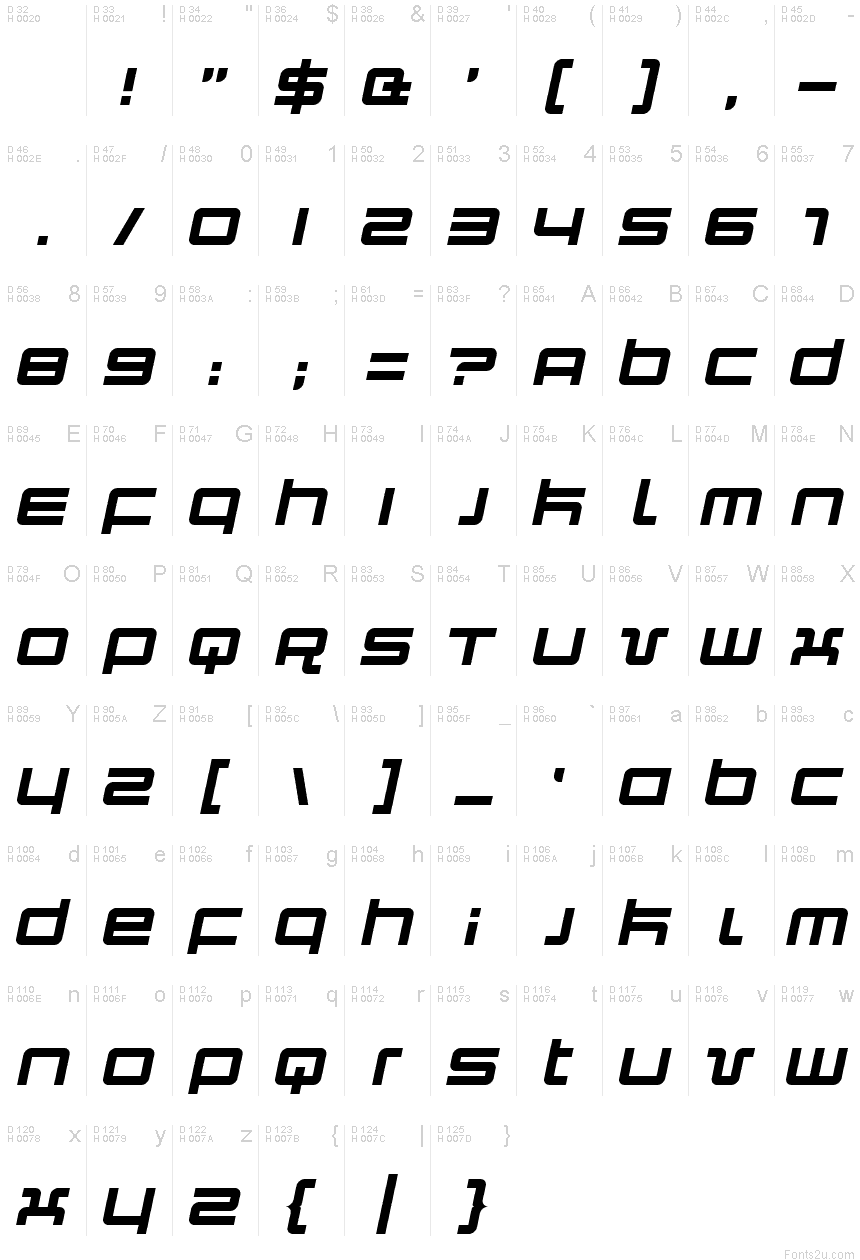
Quark Italic, realizzata da dustBUST Fonts, è un carattere display corsivo futuristico e gratuito, caratterizzato da una silhouette snella e tagliente. Le lettere sono ridotte all'essenziale: forme squadrate, angoli smussati e lunghi tratti angolati le conferiscono un'estetica techno anni '90 che trasmette dinamismo anche da ferma.
Si adatta perfettamente a loghi di videogiochi, flyer di musica elettronica, packaging sci-fi, titoli di interfacce e schermate di apertura, dove un carattere gratuito con una tale inclinazione è in grado di definire il mood da solo. Usalo per branding essenziale, titoli di copertina o nomi di prodotto se vuoi un lettering dall'aspetto aerodinamico, sintetico e leggermente sospeso.